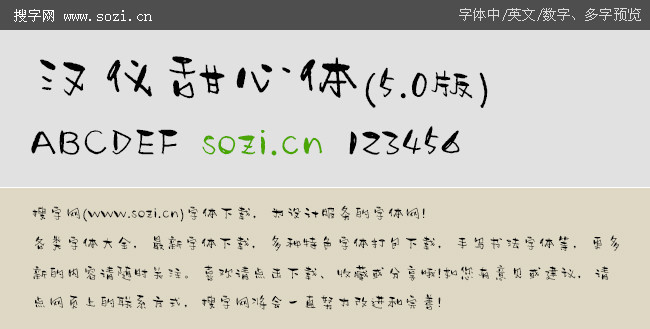
漢儀甜心體5.0
搜字網(wǎng)提供一款漢儀甜心體5.0中文字體下載,漢儀甜心體是漢儀字庫(kù)設(shè)計(jì)的一款非常個(gè)性的字體,并在七夕節(jié)發(fā)布,這款字體略帶搞笑的氣息,有的筆畫粗,有的筆畫細(xì),但是每一個(gè)筆畫都不規(guī)整,休閑程度比較高,如果用在非常甜蜜的文字上面,效果非常好,能夠適用于藝術(shù)設(shè)計(jì)、包裝印刷、海報(bào)設(shè)計(jì)、圖形設(shè)計(jì)等領(lǐng)域。(如需要商用請(qǐng)聯(lián)系漢儀字庫(kù)購(gòu)買版權(quán))